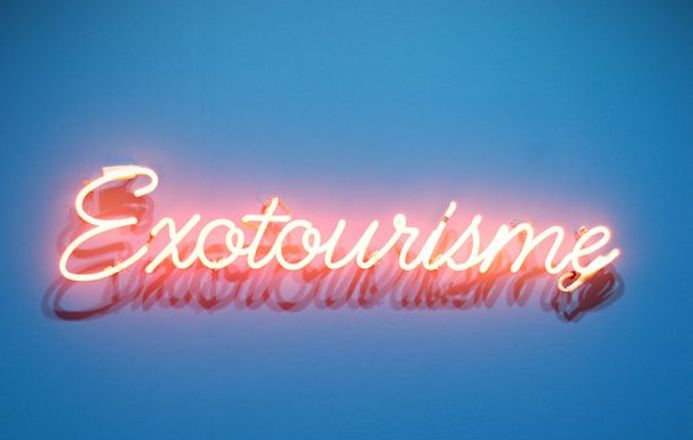
Les néons jouent avec la lumière et les couleurs flashy pour créer de belles typographies !
Outre celles de Drive, on pense notamment aux diners américains qui en ont fait leur marque de fabrique...
Bref, une sélection de typographie lumineuse !